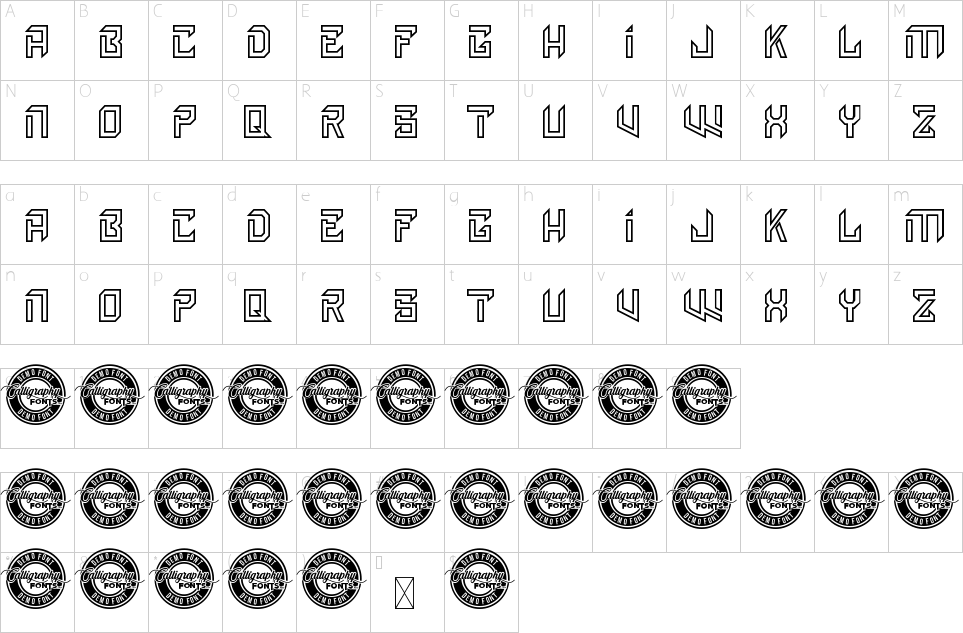
Discrown Font – Fonte Grátis
Discrown Font
Descubra a beleza única da Discrown Font, uma elegante fonte criada pelo designer chamado calligraphyfonts que você pode descarregar gratuitamente para uso nos sistemas Windows e Mac. Esta fonte é perfeita para quem busca um equilíbrio entre simplicidade e sofisticação em suas produções digitais. Com sua design de gravação, a Discrown oferece uma experiência visual única e envolvente. Quem procura por fontes com uma aparência moderna e contemporânea, mas que não perde a elegância tradicional encontrará nesta fonte a solução ideal. Com apenas duas letras do seu nome, você terá acesso à riqueza de expressões e personalidades que a Discrown Font tem para oferecer. Descarregue já e experimente uma nova maneira de expressar sua identidade visual!